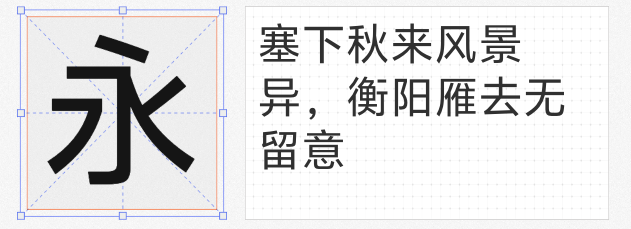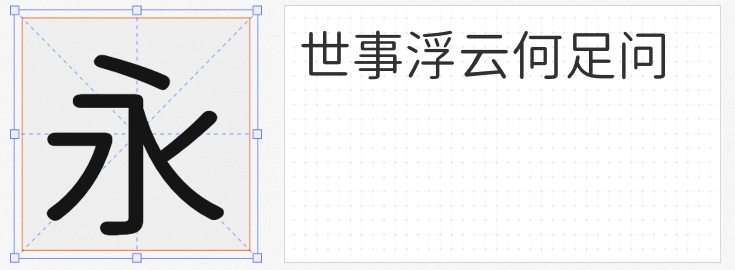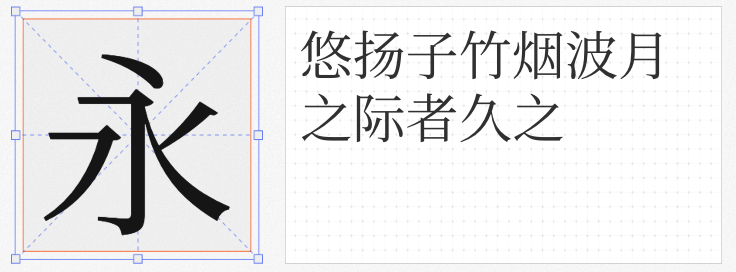
在多元设计场景中,一款优秀的中文字体需兼顾简体繁体全覆盖、视觉呈现力与商业使用自由度。本文精选四款免费可商用的高品质中文字库,涵盖圆黑、宋体、无衬线及现代风格,满足从屏幕显示到印刷出版的全场景需求。
1. 寒蝉圆黑体 Normal
基于思源黑体深度优化的寒蝉圆黑体,通过圆角化处理赋予字体柔和的视觉感受,同时保留黑体的清晰骨架。其繁简字库完整覆盖GBK标准,字形结构严谨,笔画粗细均匀,尤其适合科技、教育类设计项目。圆角细节在保持现代感的同时,弱化了黑体的机械感,成为UI界面与品牌标识的实用选择。
2. 昭源宋体 Regular
作为昭源黑体的配套宋体,昭源宋体以7种字重构建丰富层次体系,横细竖粗的经典结构中融入现代设计语言。其最大亮点在于超大字库(支持CJK扩展G区)与屏幕优化技术,即使在小字号下仍保持清晰可读性。繁简无缝切换的特性,使其成为出版物、长文本排版的专业之选。
3. vivo Sans Regular
这款为移动阅读优化的字体,通过0.5mm级的笔画微调实现视觉重心平衡。去装饰化的设计理念下,中宫适度开放提升小字号识别度,而字面框的黄金比例确保多语言混排时的和谐感。其繁简版本均采用相同结构逻辑,特别适合需要跨国传播的品牌视觉系统。
4. 阿里巴巴普惠体 3 65 Medium
以"少年感"为核心设计理念的阿里巴巴普惠体3.0,通过87%的字高占比与15°倾斜衬线营造向上动势。标题字省略出脚的设计简化视觉负担,65字重则在标题与正文字重过渡中取得完美平衡。其繁体版本同步优化了港澳台地区的用字习惯,成为电商、文创领域的首选品牌字体。